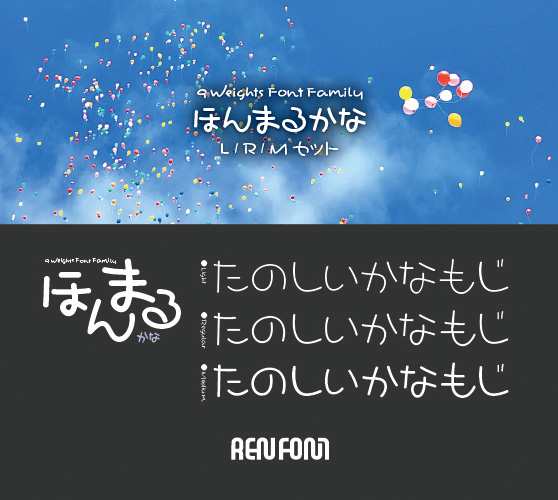
手書き風書体
ほんまるかな-テキスト用3ウェイトセット(L/R/M)
HommaruKana-L,HommaruKana-R,HommaruKana-M
かすかに筆文字の名残り、味わいのある丸もじ。やや左上に重心がある独特のフォルム。既存の他社丸ゴシックと組み合わせても違和感なく溶け込み、あたたかな雰囲気を醸し出します。
縦組み・横組みのすべての文字にペアカーニングをほどこしており、メトリクス処理をするだけで、バランスのとれた組みが得られます。テキスト用3ウェイトセット。